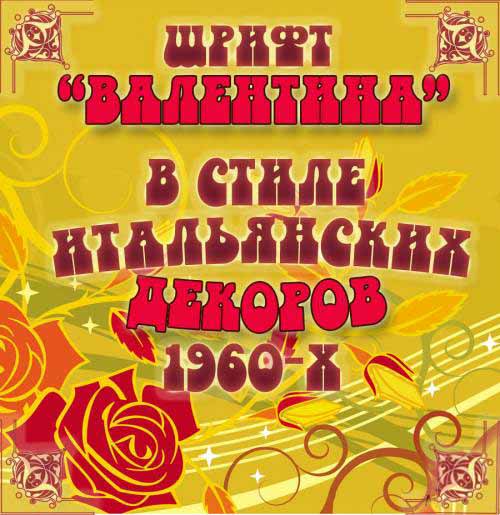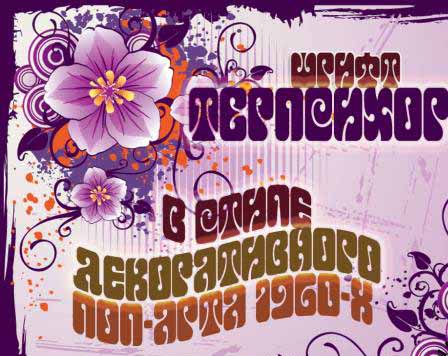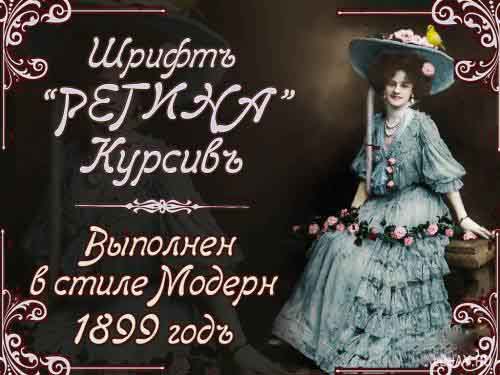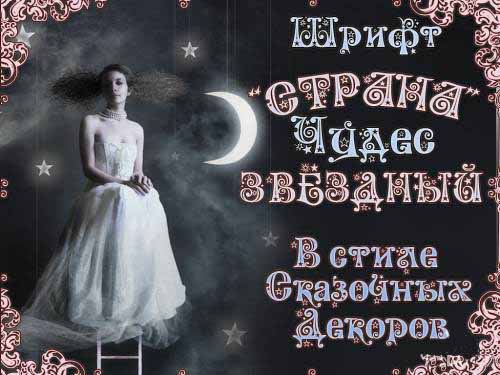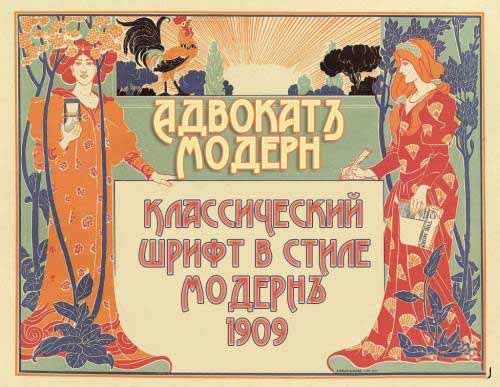
Винтажные русские шрифты Часть 4
В четвёртую часть Русских Винтажных шрифтов от А.Гофманн вошли:
Wonderland (2 начертания Normal и Stars)
Regina Kursiv (классический курсив эпохи Модерн)
Advokat Modern
Terpsichora (шрифт в одном из стиле многоликого Поп-арта :)
Valentina (стилезованный под 1960-ые гг. "Итальнский" шрифт)